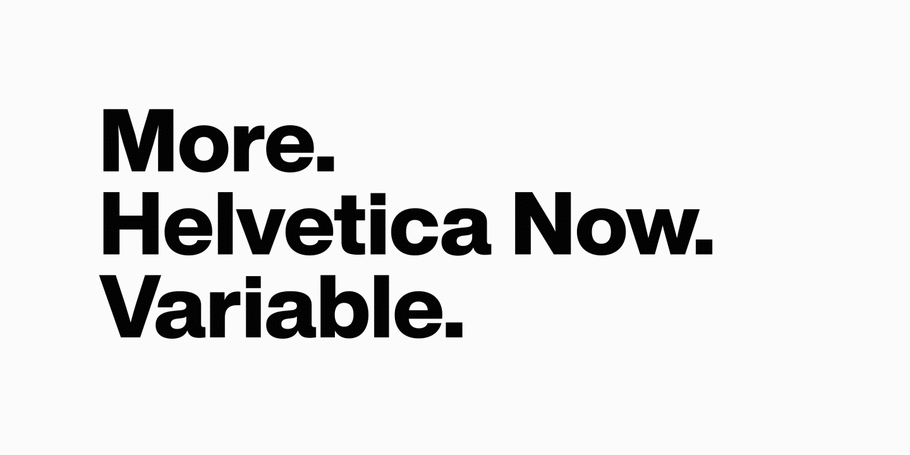
Mais de tudo, para todos. Apresentando Helvetica Now Variable.
As fontes variáveis em geral – e a Helvetica Now Variable em particular – irão remodelar o conceito do que significa a palavra ‘fonte’.
A Helvetica Now Variable, novidade do Monotype Studio, oferece mais de um milhão de novos estilos Helvetica em um arquivo de fonte de última geração, permitindo que você crie tons infinitos de expressão, animações tipográficas incríveis e tipografia ultrarrefinada.
Dois anos se passaram desde que o Monotype Studio lançou a Helvetica Now, uma atualização querida e muito aguardada do design atemporal e onipresente de 1957 de Max Miedinger. Esse projeto reimaginou a Helvetica para um mundo que nem Miedinger nem a equipe por trás da reformulação da Neue Helvetica nos anos 80 poderiam ter planejado: um mundo que exige legibilidade nítida em telas pequenas, enormes outdoors de LED e inúmeros pontos de contato entre eles.
Bem, adivinha? Não terminamos.
Se a Helvetica Now trouxe o design de Miedinger para o nosso presente digital, a Helvetica Now Variable o lança para frente em um futuro amplo e aberto. É um salto evolutivo para uma fonte que sempre esteve um passo à frente de seu tempo.
Os consumidores de hoje esperam que o branding seja distinto, dinâmico, personalizado e tenha um carregamento ultrarrápido na Web, onde quer que eles estejam e em qualquer dispositivo que estejam usando. A Helvetica Now Variable foi construída para atender a essa demanda – um arquivo de fonte com milhões de estilos que seja incrivelmente rápido e poderoso, além de surpreendente e divertido. (Sim, milhões – o espaço de design variável de três eixos oferece 1.235 milhão de variações, para ser preciso.)
Ao contrário dos formatos de fonte convencionais que exigem que cada estilo dentro de uma família seja um arquivo separado, as fontes Variable empacotam todo o DNA necessário para cada estilo em um único pacote organizado. E como esse único arquivo contém o DNA da família, os designers podem percorrer toda a sequência, misturando, combinando e personalizando variações sobre o tema da família. Agora é possível ajustar uma variação hiperespecífica ou até mesmo animar o movimento de um estado, peso, largura ou tamanho para o próximo, tudo a partir de um arquivo com uma fração do tamanho das fontes estáticas combinadas.
“Esta é a Helvetica no alvorecer de uma nova era no design e na tipografia”, diz Charles Nix, diretor criativo da Monotype. “As fontes variáveis em geral – e a Helvetica Now Variable em particular – irão remodelar o conceito do que significa a palavra ‘fonte’.”
A Helvetica Now Variable também inclui as novas larguras Comprimida e Condensada, que oferecem aos designers e marcas uma vasta quantidade de estilos para escolherem ao adicioná-las às variações existentes de peso e tamanho óptico (144 instâncias “marcadas”). Isso se baseia nas adições de tamanhos ópticos e conjuntos de caracteres expandidos no lançamento de 2019, resultando na expressão mais completa e refinada já apresentada da Helvetica.
Há dois anos, quando lançamos a Helvetica Now, dissemos que ela era “tudo o que amamos na Helvetica e tudo o que precisamos para a tipografia dos dias de hoje”. Não se tratava de um “relançamento” ou uma “restauração”, mas uma afirmação sobre o lugar da Helvetica em um mundo que mudou e continua mudando.
A Helvetica Now Variable não é meramente uma continuação desse projeto – ela divide o átomo da Helvetica Now e libera profundidade, dimensão e possibilidade sem precedentes. Ela oferece mais Helvetica do que nunca. Mais liberdade para experimentar. Mais formas de expressar. Mais poder para criar experiências memoráveis.
“A Helvetica Now Variable convida os designers a pintarem com a fonte”, diz Nix. “Para liberar novos modos de expressão tipográfica e ir além do que as gerações anteriores de tipógrafos achavam possível.”